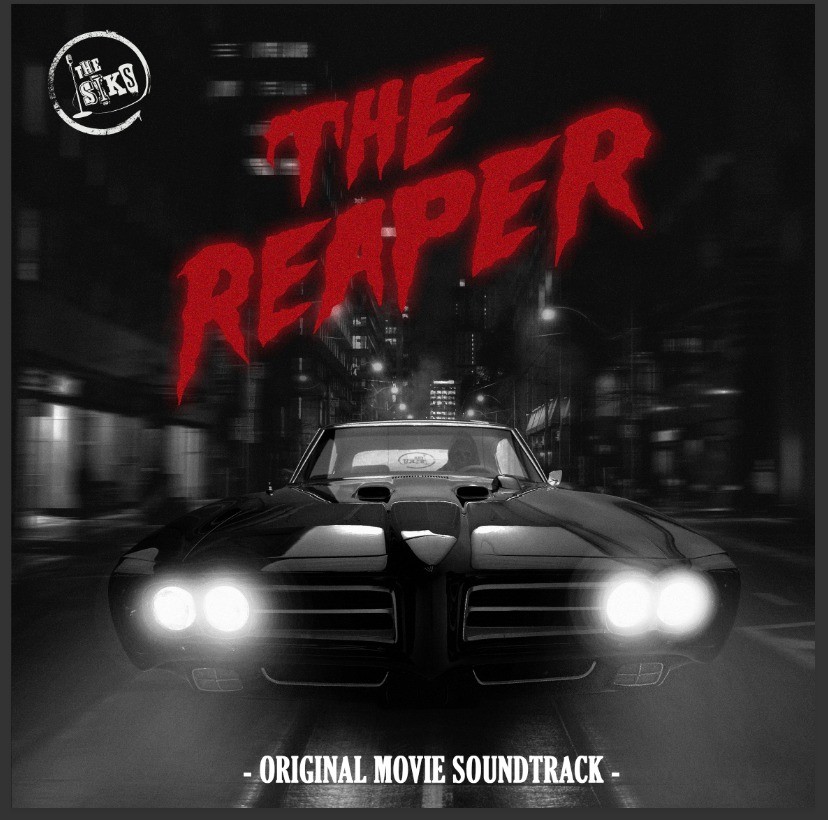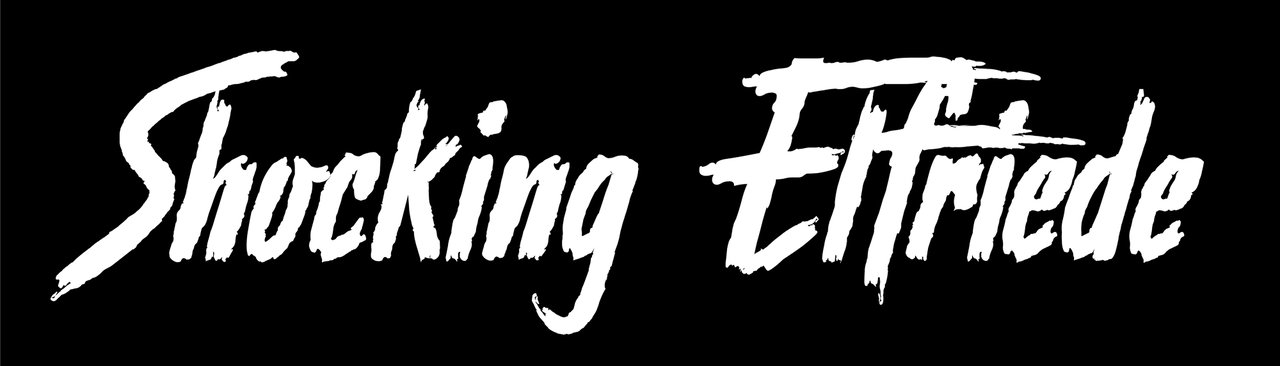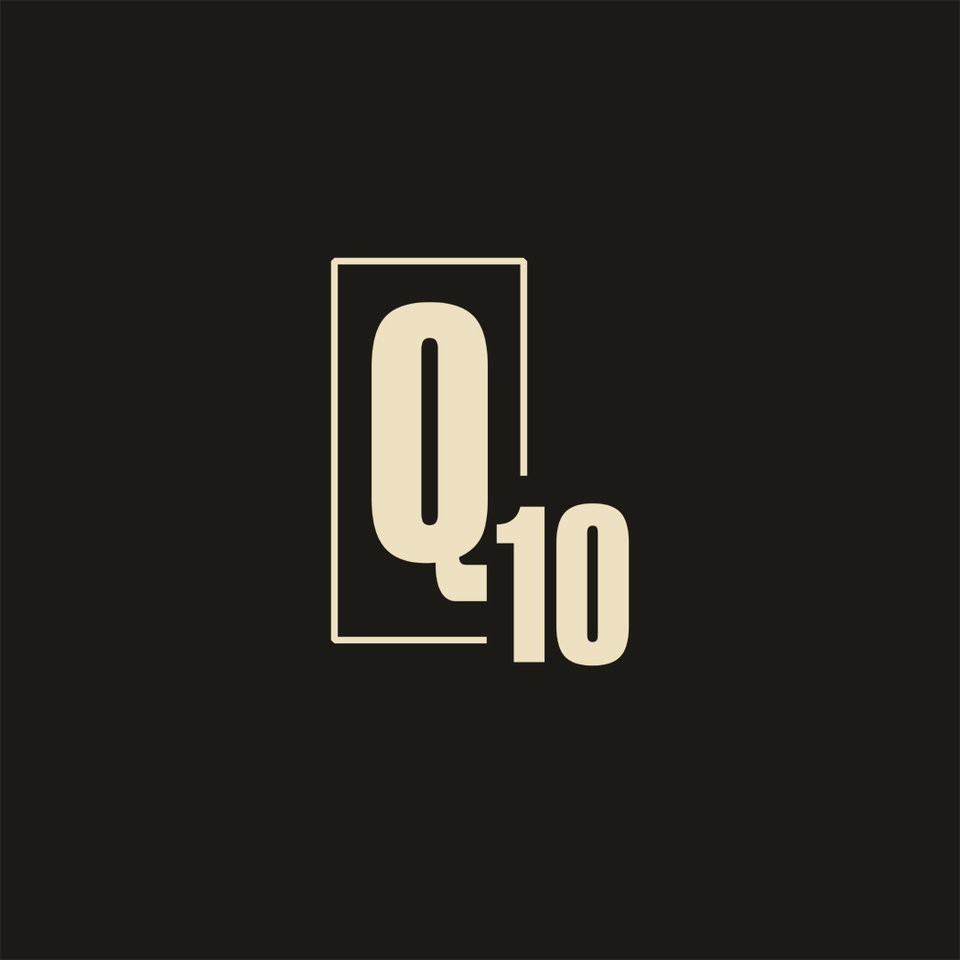
Euer Bandlogo-Artwork-Schriftart... her damit...!
Das gefällt mir. Sieht aus wie von einem Groschenroman oder einem Kinoplakat aus den Fünfzigern...
Der Peitschenaugust mit der Zibblmütze?
Unsere nächste Single bekommt ein Video wie eine Filmvorschau und ein imaginäres Filmplakat. Halt nicht Der Wixxer sondern der Reaper. :D
Klasse das Ding. :great:
Und in was fürn geilen Steinbruch habt ihr denn "Jumpin Jack Flash" aufgenommen?
Dafür haben wir keine Kosten und Mühen gescheut und sind glatt 30 Kilometer gefahren! In die Nähe von Meiningen/Thüringen. Halt, ich meinte natürlich den Grand Canyon! :bier::rock:
Das war vorgestern 30 Kilometer in die andere Richtung. Eine schöne Gegend haben wir schon!
Wir hatten auch das erste Mal die Rollups im Einsatz. Bei einem 45-Minuten-Slot sind die Gold wert. Aufgebaut in 1 Minute und man hat ein brauchbares Bühnenbild. Ich möchte nichts über den Cliptuner des Gitarristen hören! :W
Zurück zum Thema: auf Anraten unseres Designmenschen haben wir die Rollups weiß auf schwarz bestellt. Das war die richtige Entscheidung. Es fallen dann die Aufdrucke ins Auge und nicht die hellen Vierecke der Stoffleinwand. Auch bei wechselndem Bühnenlicht bleibt das so. 130 Euro pro Stück brutto, in 20 Sekunden aufgebaut.
Kann ich nur ausdrücklich bekräftigen. Weiße Flächen haben (zumindest auf "dunklen Rockbühnen") da nix verloren.
Bei uns ist das Logo schon seeehr reduziert...
Das ist das nüchterne offizielle...
Anfänglich hatte ich mal sowas vor... Eigentlich phonetisch das Gleiche, aber es erinnert doch etwas zu sehr an "United Four"
Fangen meine ernst dreinblickenden Kollegen aber nicht ganz so lustig :-)
Atom Heart Mother?
Das wäre ja noch eine Ehrung.. Bezog sich phonetisch auf Q10 = Kuh 10 :-)
Aber eine Ähnlichkeit zum PF-Cover ist schon da ;-)... aber nicht beabsichtigt gewesen...